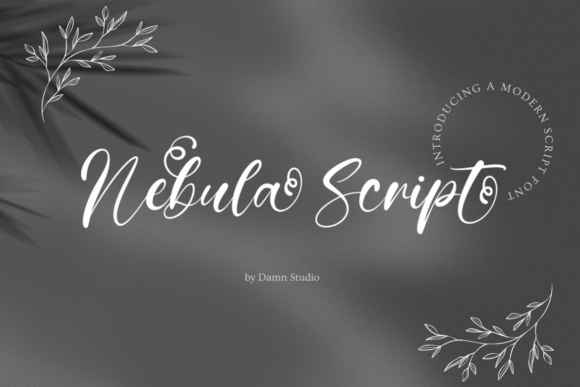
Nebula Script
Якщо ви шукаєте високоякісні ресурси, такі як Nebula Script, цей преміум-пакет є фантастичним вибором для ваших творчих проектів.
Незалежно від того, чи створюєте ви продукти POD (друк на вимогу), весільні запрошення або графіку для соціальних мереж, Nebula Script стане ідеальним вибором.